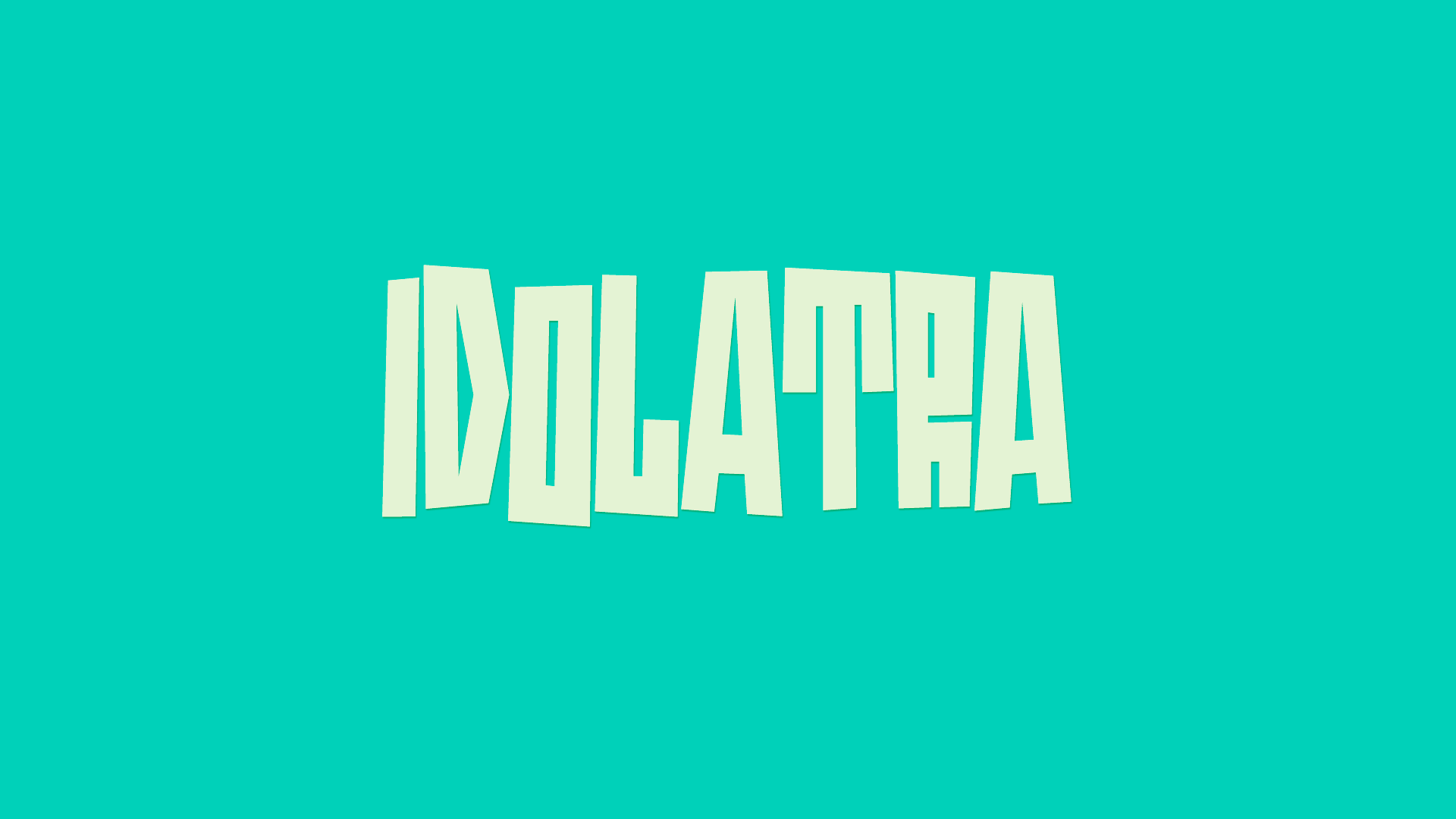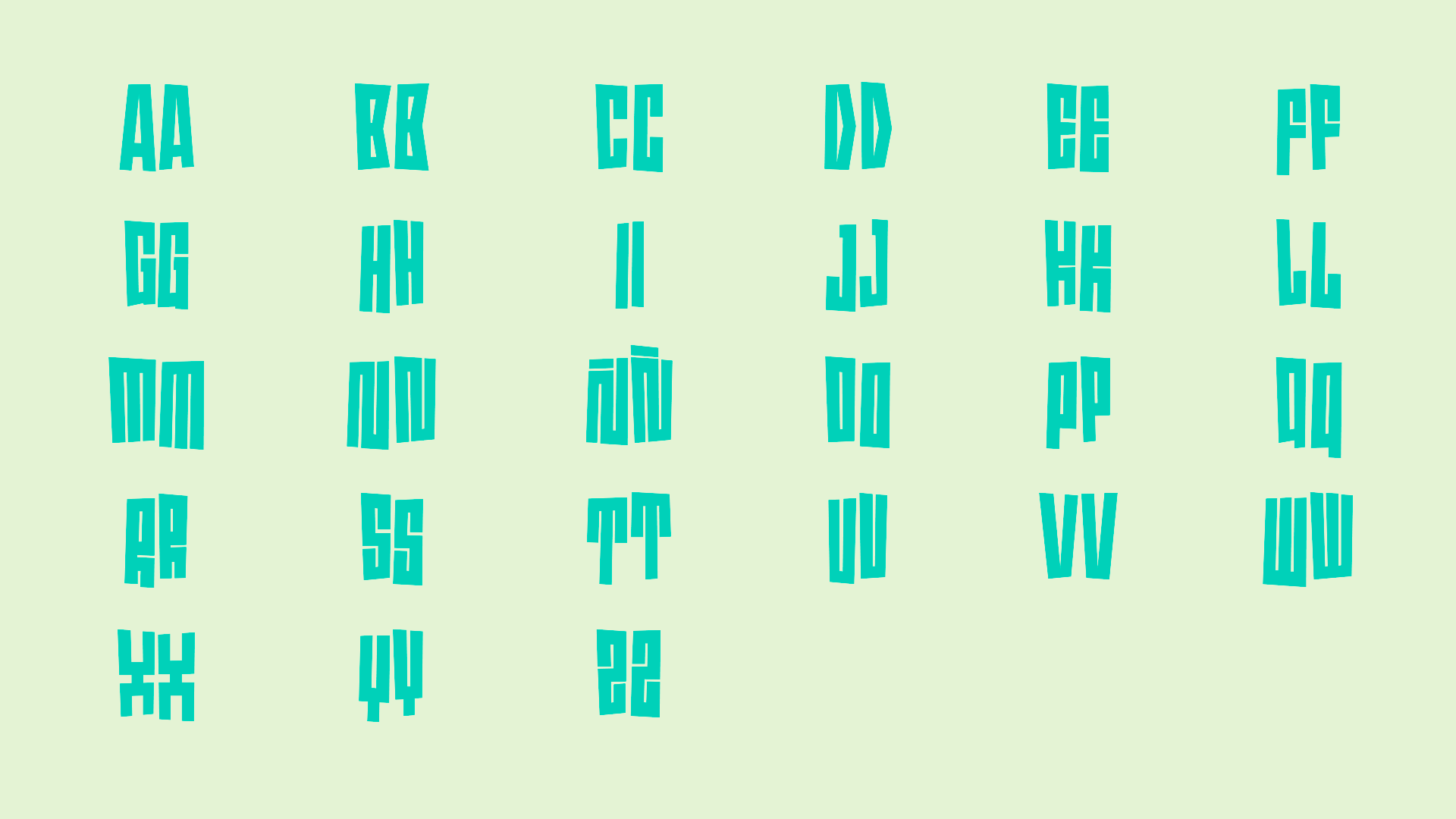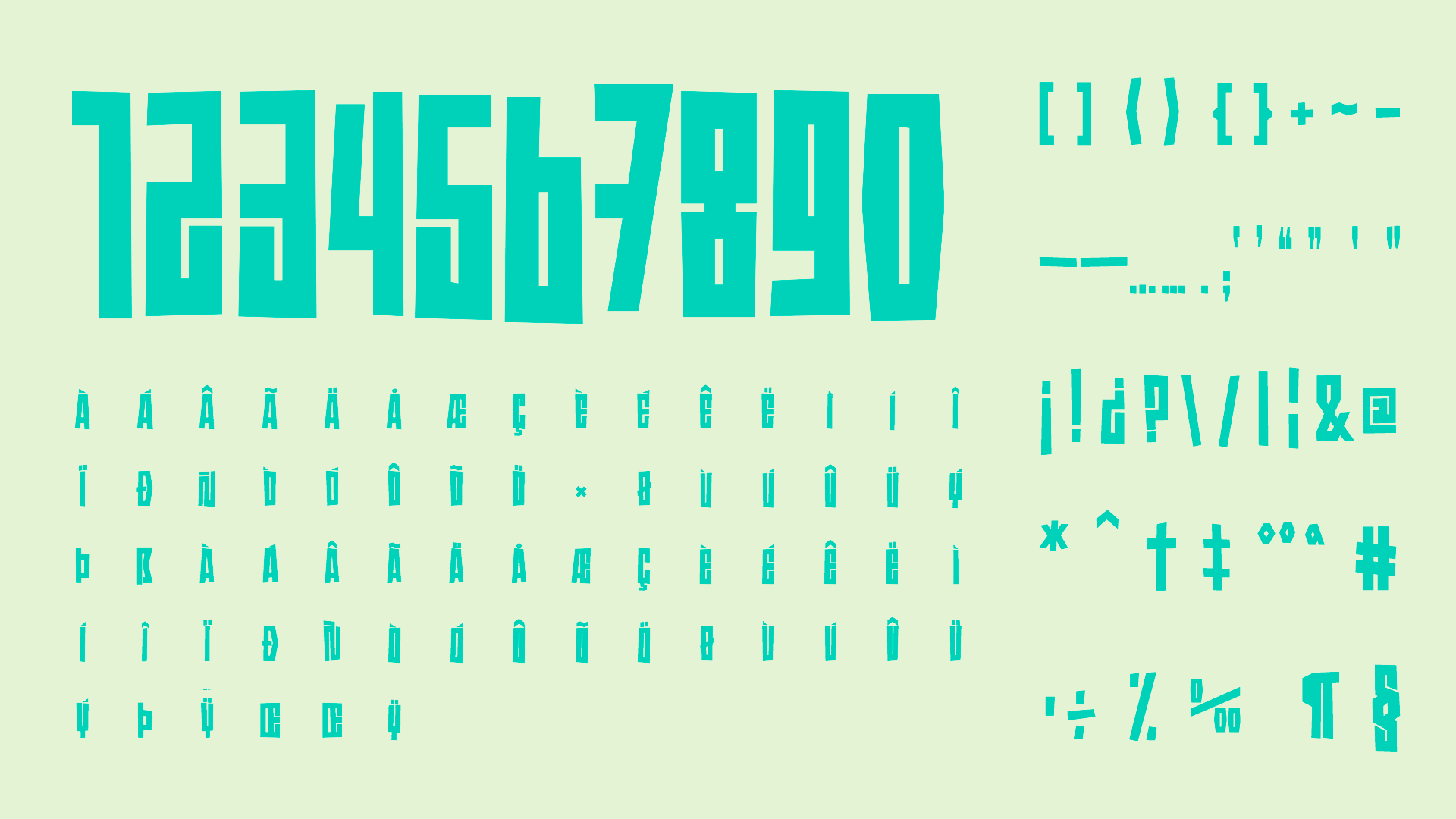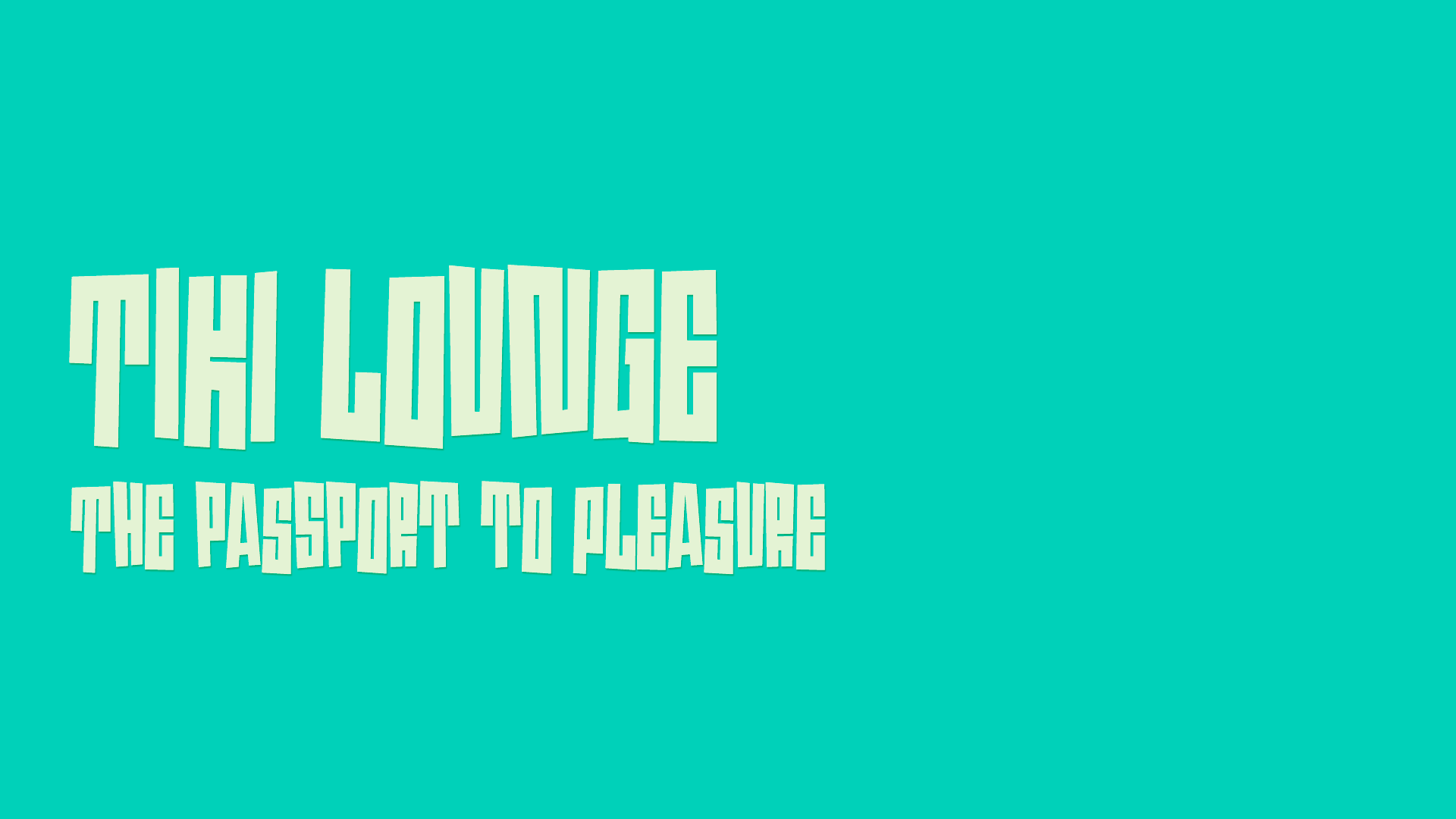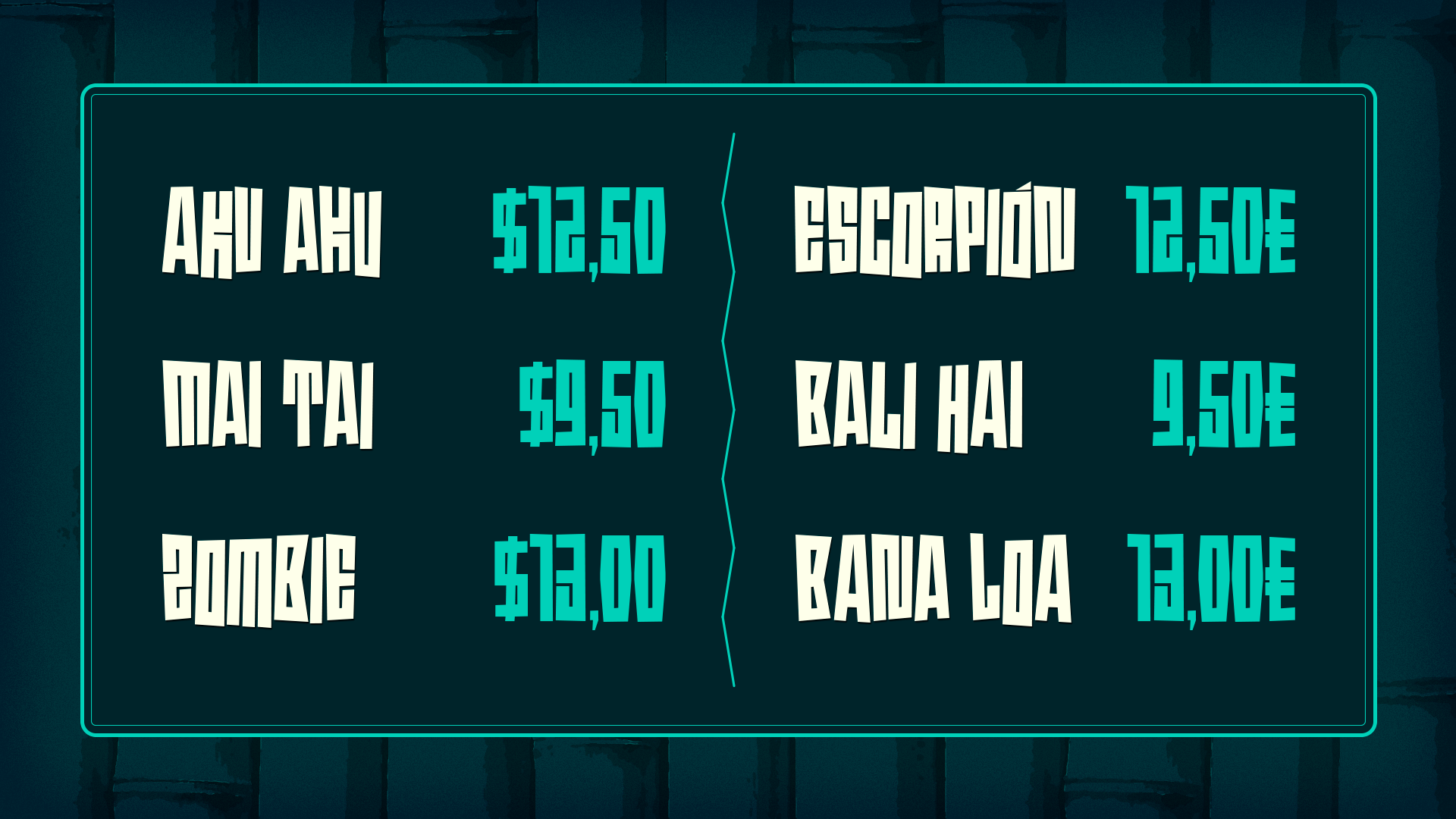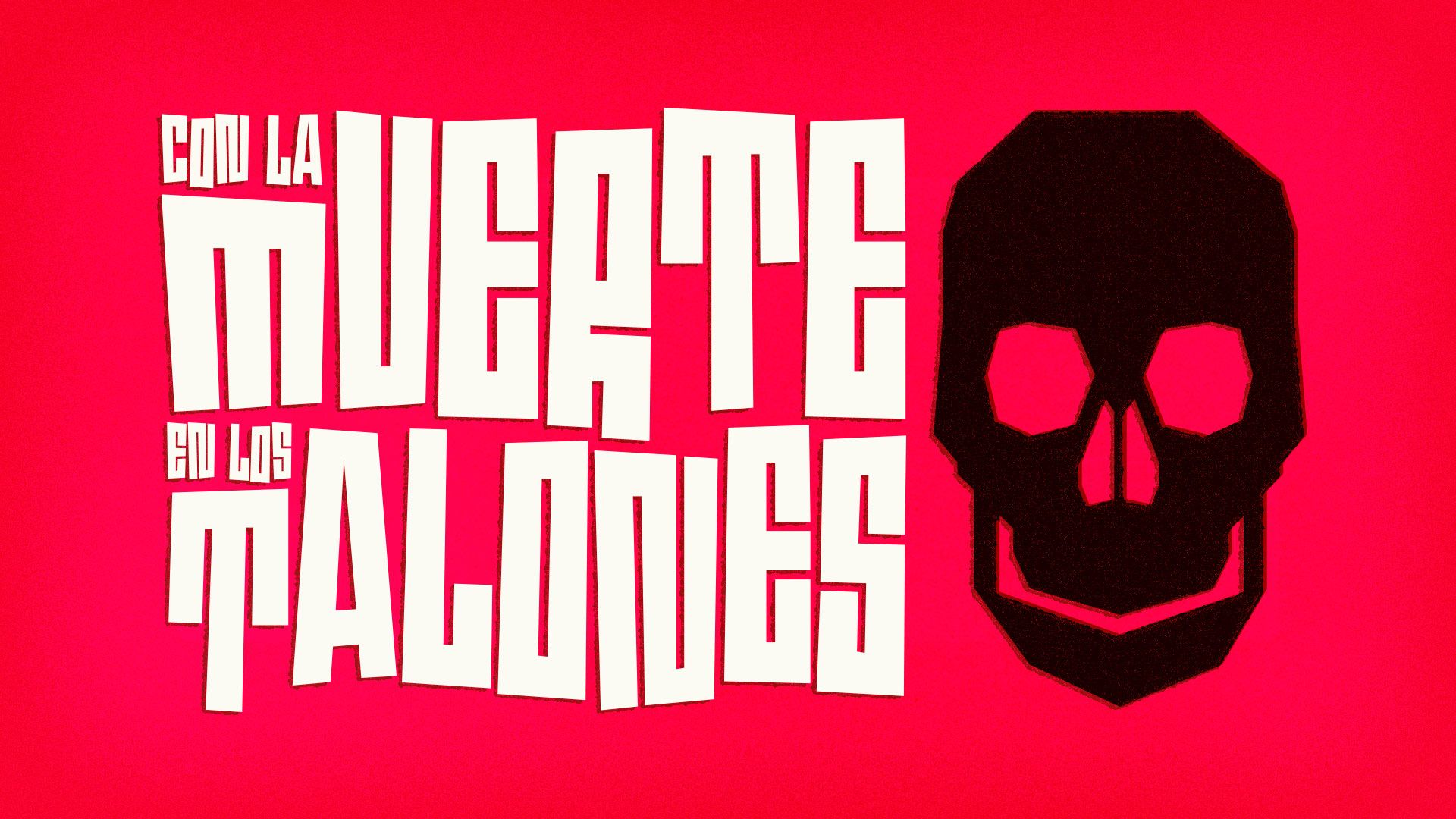
Muy chula... Enhorabuena.
Increible! Felicidades!
Mola!!
yeah!!! muy guapo!!
¡Muy chula!
Que cuca!, la veo muy tiki! ^^
Preciosa y clara- Felicidades